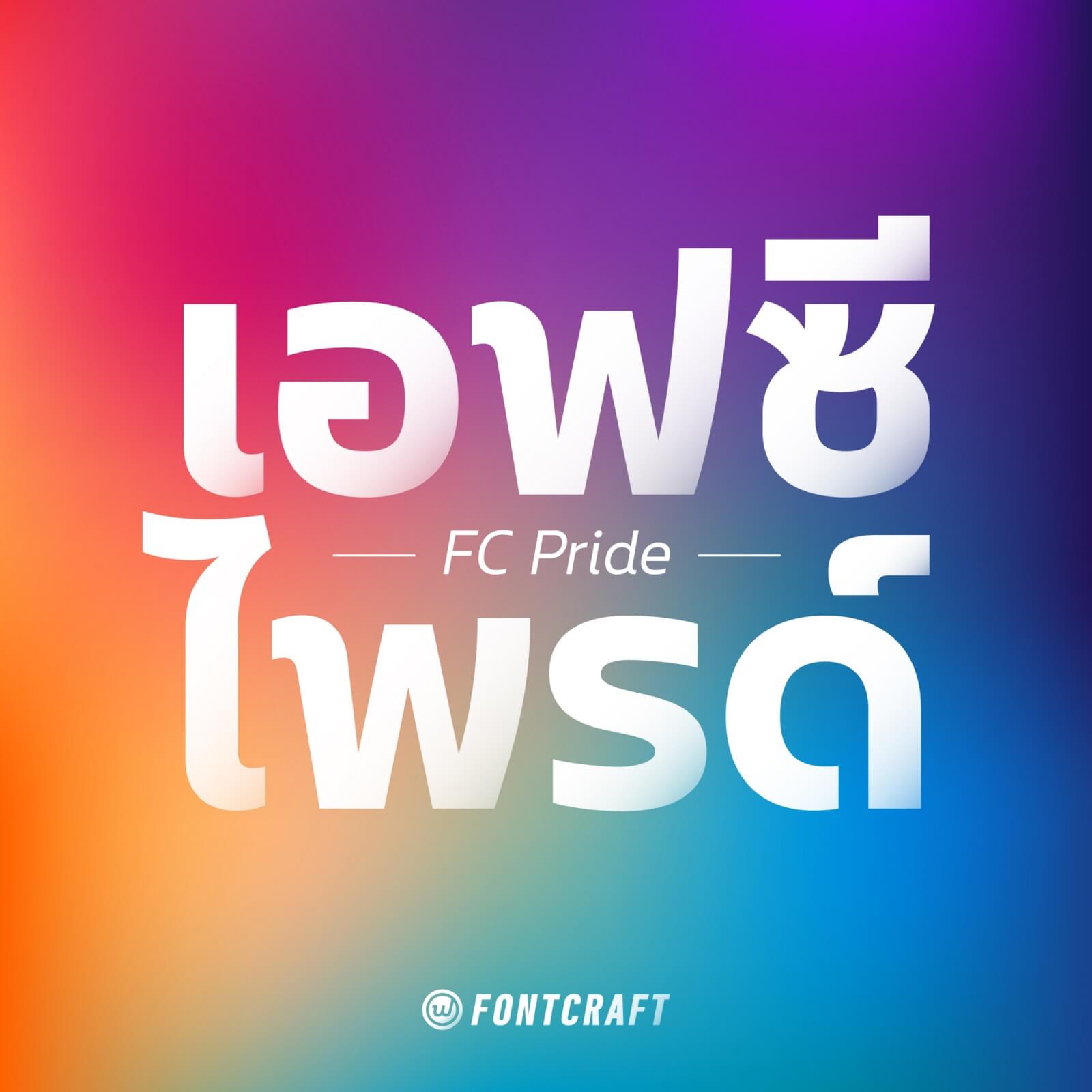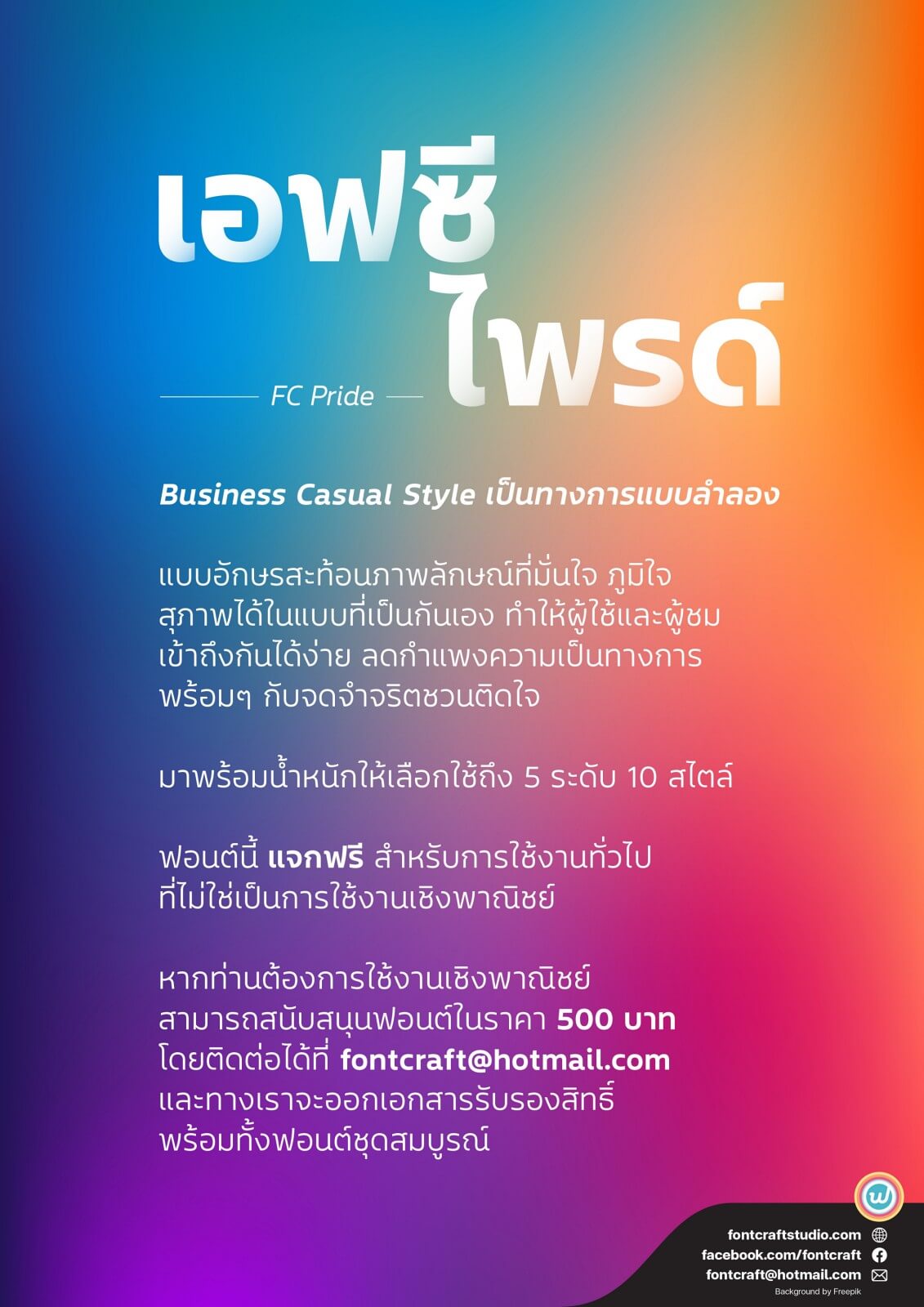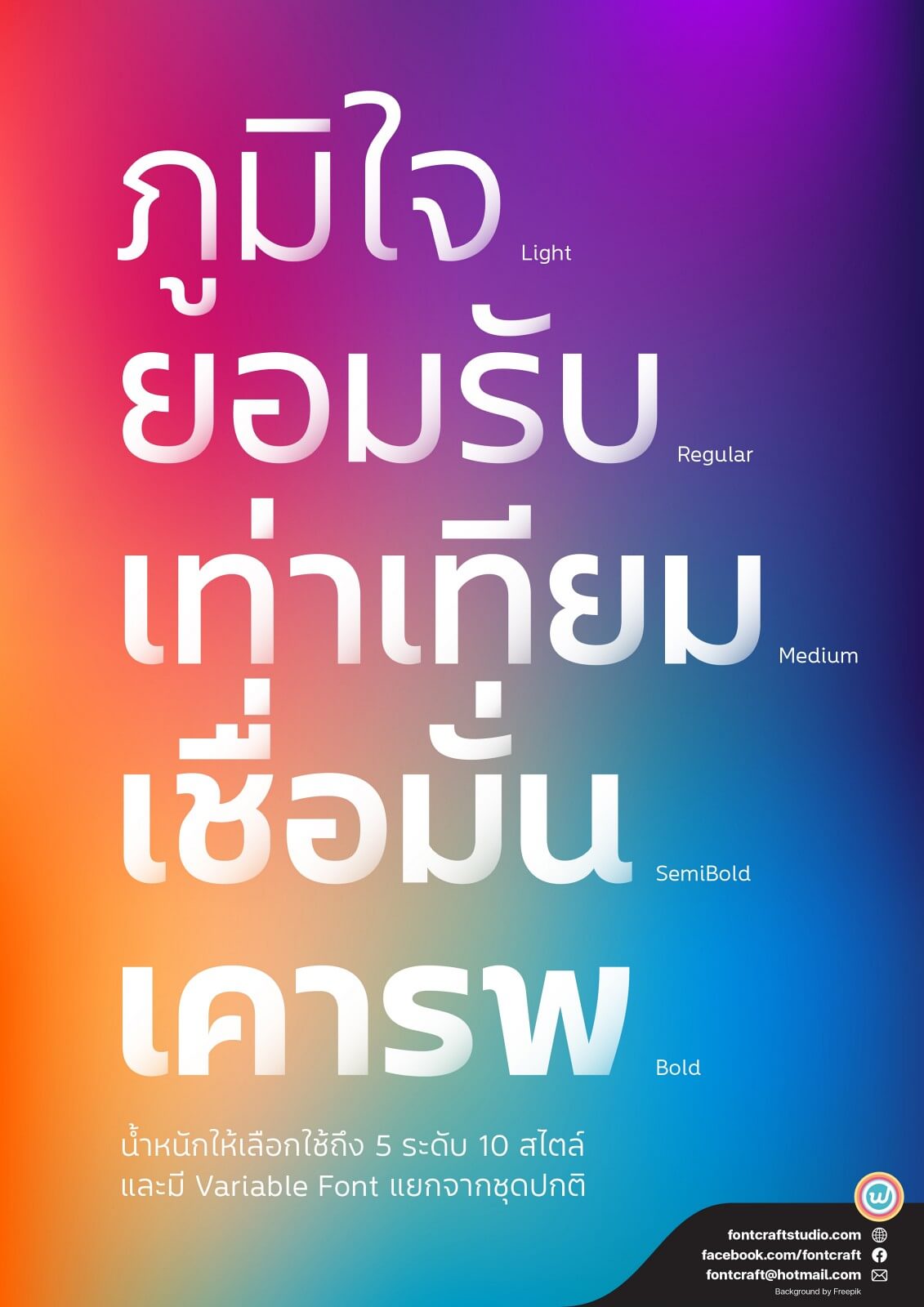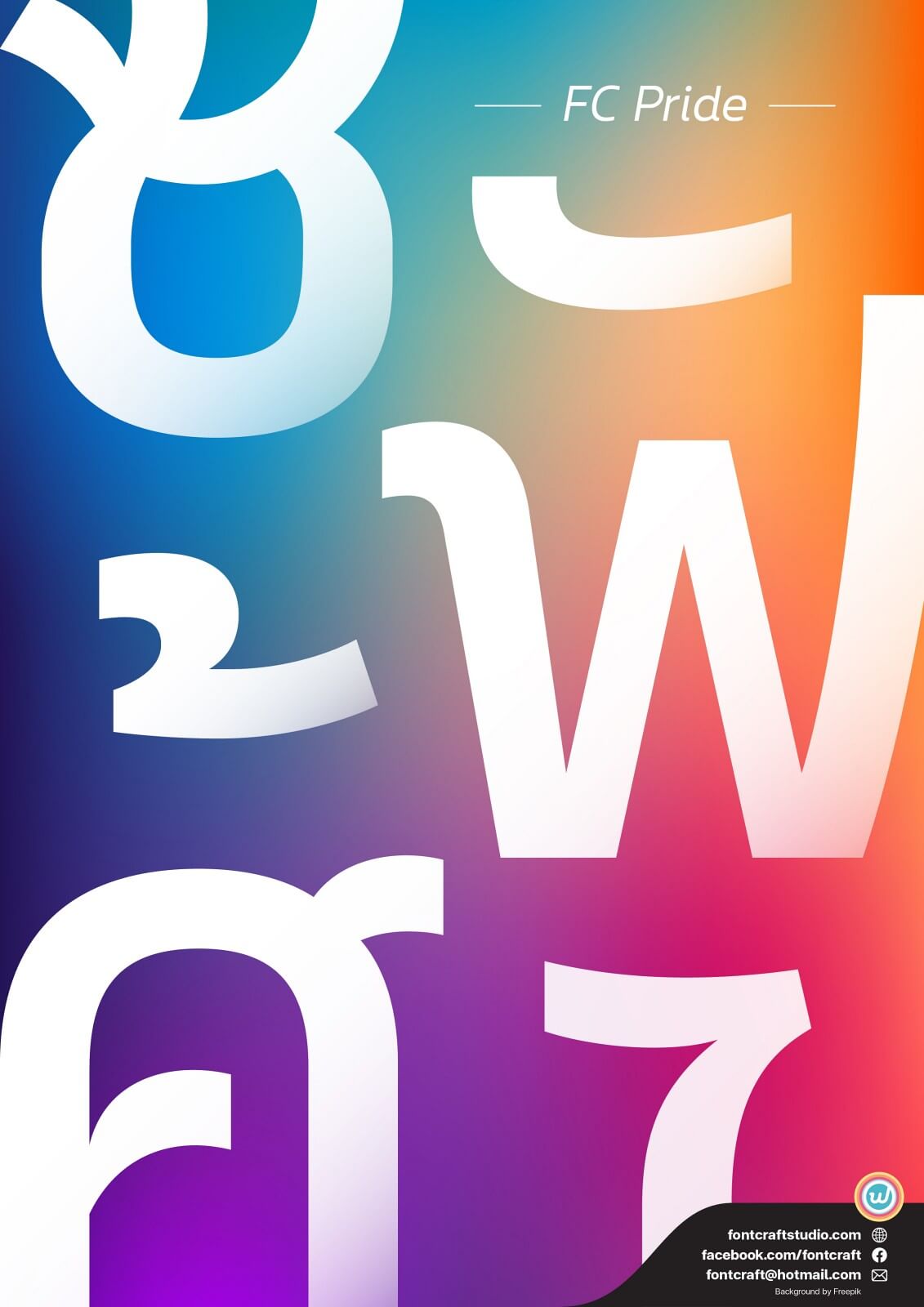
Business Casual Style เป็นทางการแบบลำลอง – แบบอักษรสะท้อนภาพลักษณ์ที่มั่นใจ ภูมิใจ สุภาพได้ในแบบที่เป็นกันเอง ทำให้ผู้ใช้และผู้ชมเข้าถึงกันได้ง่าย ลดกำแพงความเป็นทางการ พร้อมๆ กับจดจำจริตชวนติดใจ